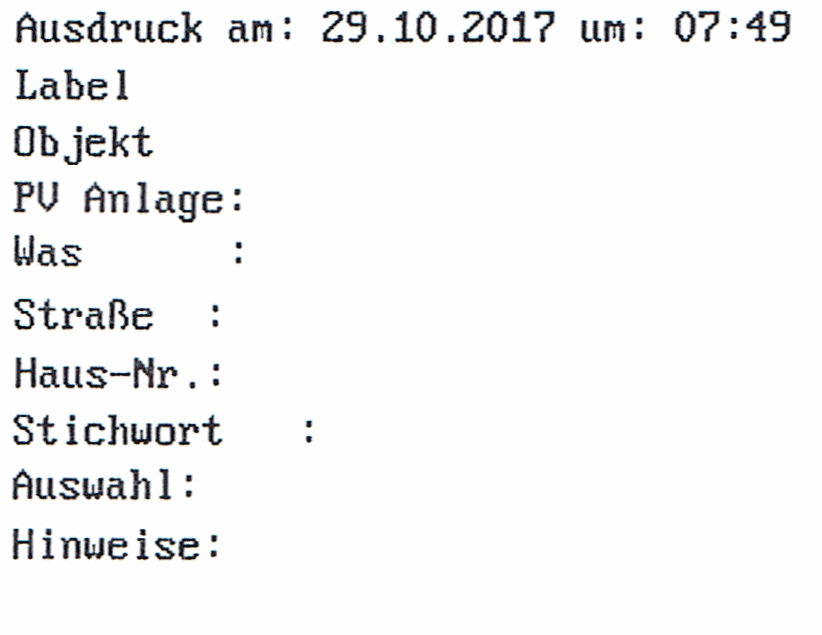
Welche Schriftart ist das?
Kann mir vielleicht jemand sagen, um welche Schriftart es sich hier handelt?
sämltiche Webseiten zur Font-Erkennung lieferten nicht das korrekte Ergebnis.
Sieht ja etwas antiquiert aus... vielleicht errinnert sich noch jemand von den alten Hasen daran, falls die mal zu den Standard Fonts gehörte. :cool_alt:
erinnert ein wenig an einen ausdruck von einem nadeldrucker, eventuell kommst damit weiter
für mich sieht es aus wie eine Konsolenausgabe. Die änlichste die mir hierzu einfällt ist Perfect-Dos-VGA auch bekannt als Raster Fonts.
Diese wird auch in der CMD genutzt.
Die Originale sind Bitmap Fonts welche in den varrois.fon files zu finden ist.
Problem hier ist aber das Diese nicht gut in Texteditoren angezeigt werden.